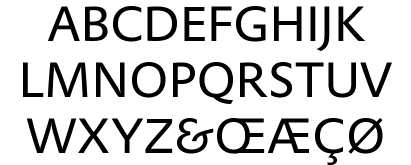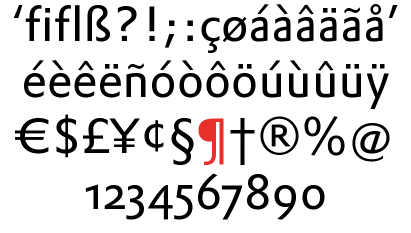
Font gesucht - "ähnlich" Scala Sans
wer kennt denn diese Schrift und kann mir vielleicht weiterhelfen. "Ähnliche" Fonts habe ich jetzt schon ein paar gefunden - aber leider nicht den exakt passenden.